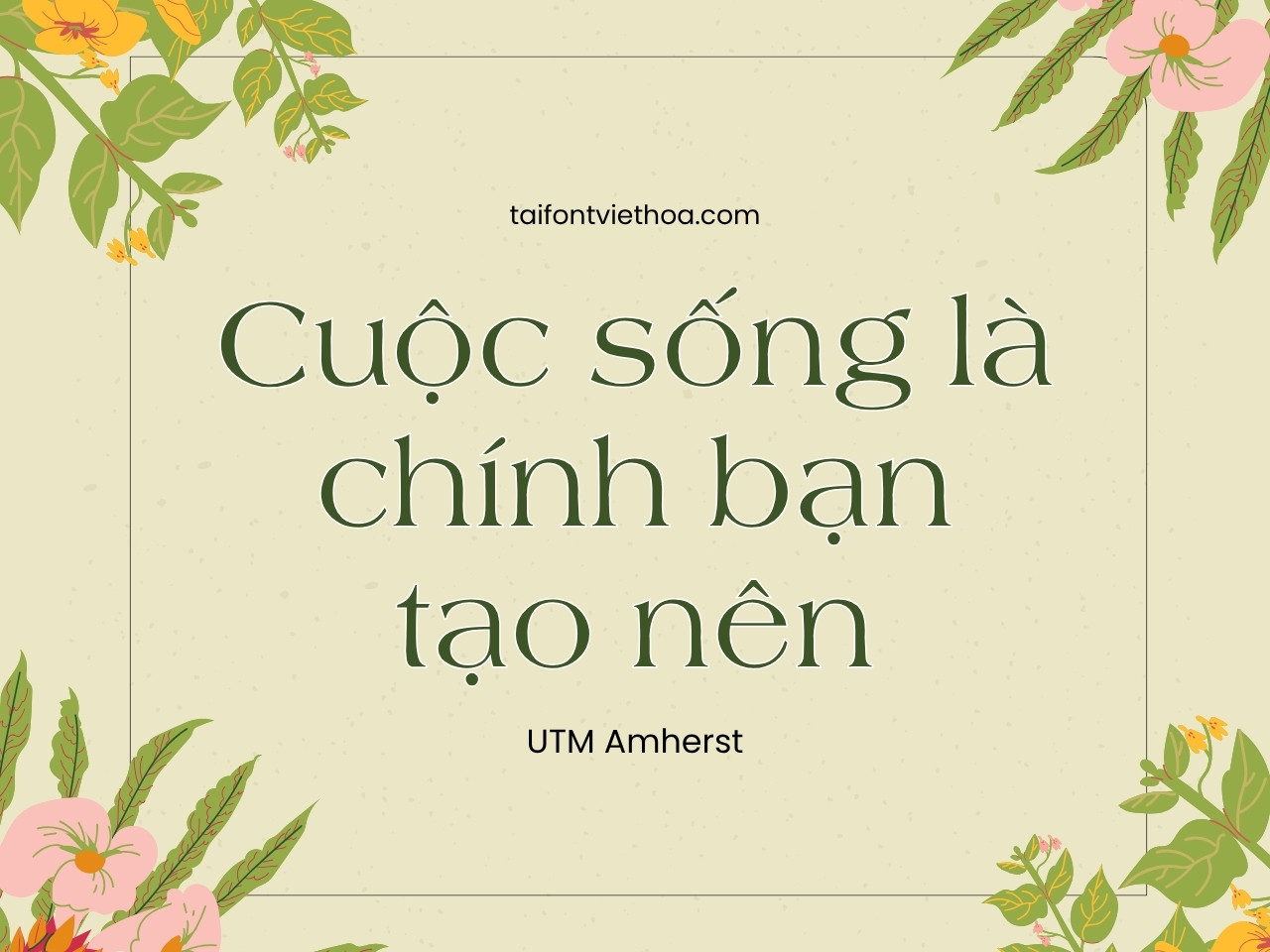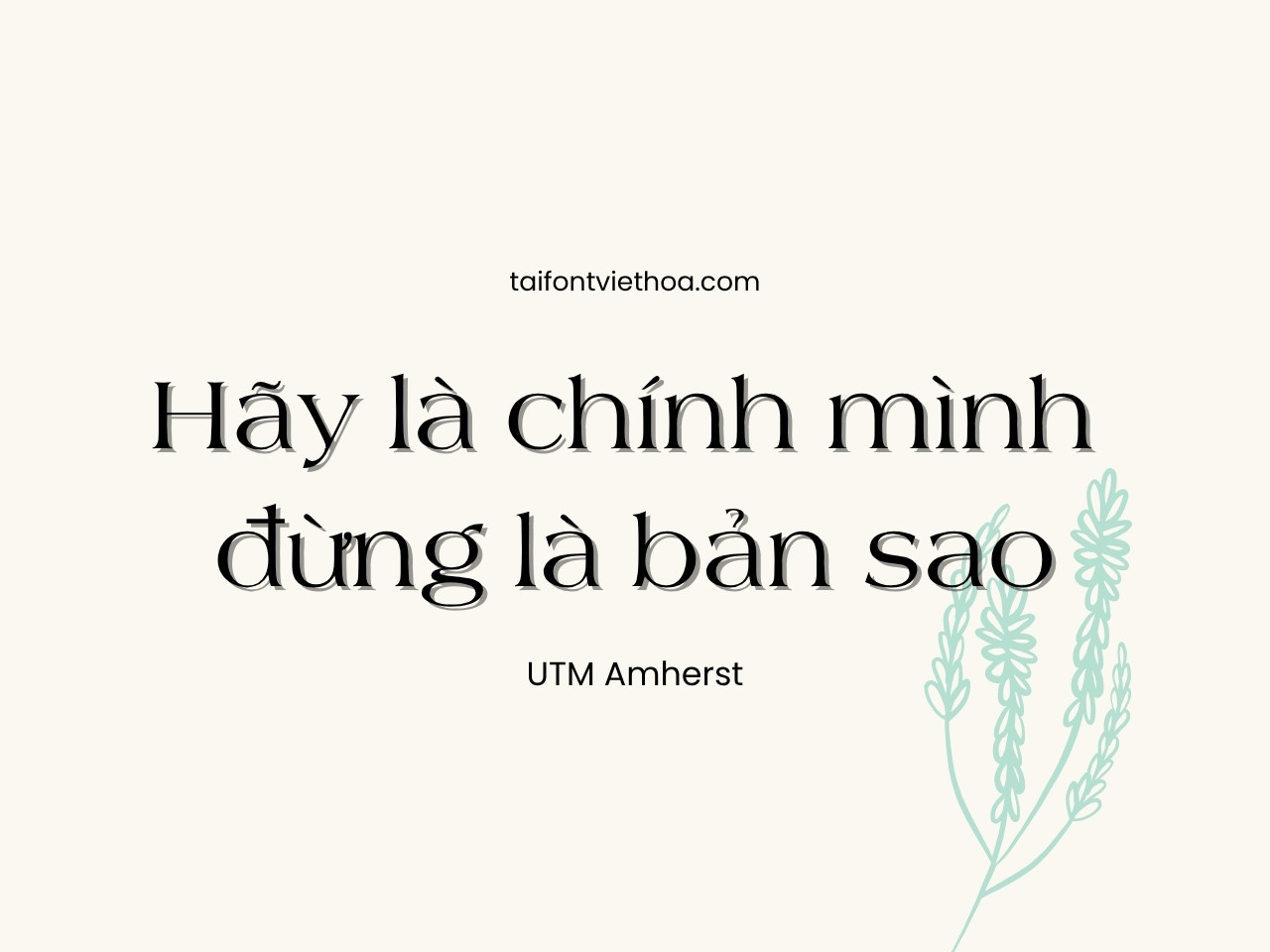
Font việt hóa UTM Amherst
Giới thiệu về font UTM Amherst
UTM Amherst là phiên bản Việt hóa của font Amherst – một kiểu chữ serif hiện đại, thanh lịch và có cấu trúc cân đối. Font gốc được thiết kế bởi nhà thiết kế Shirley Weir, lấy cảm hứng từ phong cách cổ điển pha trộn cùng sự tinh tế trong thiết kế hiện đại. Phiên bản Việt hóa đã được hoàn thiện nhằm hỗ trợ đầy đủ tiếng Việt cùng hơn 200 ngôn ngữ khác, giúp mở rộng khả năng ứng dụng trong các dự án thiết kế đa dạng trên toàn cầu.
Đặc điểm thiết kế và ứng dụng của UTM Amherst
UTM Amherst sở hữu cấu trúc serif với các nét chữ thanh mảnh, chân chữ rõ ràng và độ tương phản vừa phải, tạo nên sự cân bằng và dễ đọc. Font thích hợp cho cả văn bản dài và tiêu đề nổi bật. Ngoài ra, font còn được trang bị nhiều ligature và glyph thay thế giúp tăng tính linh hoạt trong thiết kế.
Font thích hợp cho các ứng dụng như thiết kế sách, tạp chí, thiệp cưới, danh thiếp, bao bì sản phẩm và các ấn phẩm thương hiệu cao cấp. Các ngành nghề nên sử dụng gồm: xuất bản, thời trang, tổ chức sự kiện, nghệ thuật, giáo dục và thiết kế nội thất.